Typografie Sommersemester 2011
Vom Buchstaben über das Wort zum Satzbild. Neben der Vermittlung von typografischen Grundregeln steht der experimentelle Umgang mit Schrift im Mittelpunkt.
Durch z.B. die Digitalisierung der eigenen Handschrift und Alphabet-Entwürfe auf der Basis eines Rasters wird die Sensibilität für Schrift gesteigert..
Fabian Letter
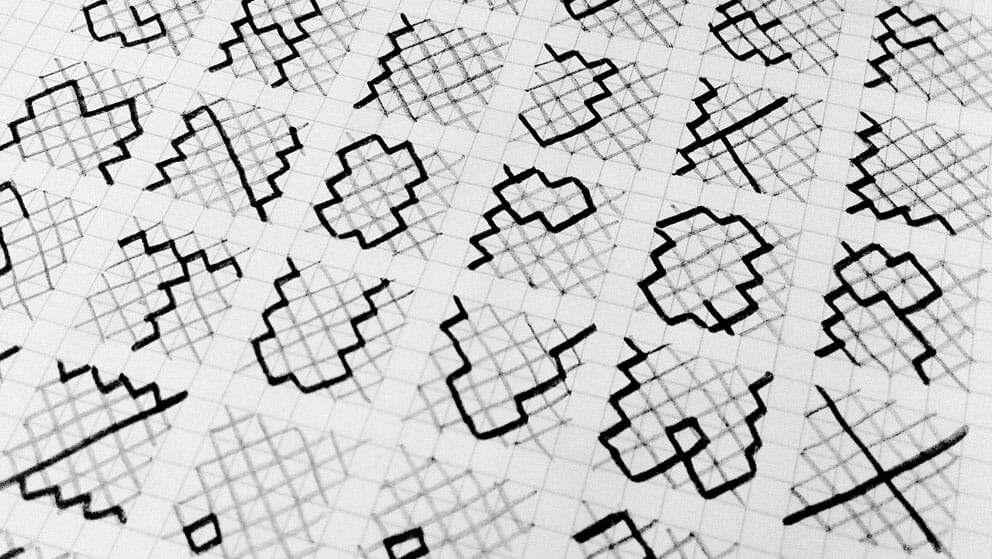
Kathrin Münsch
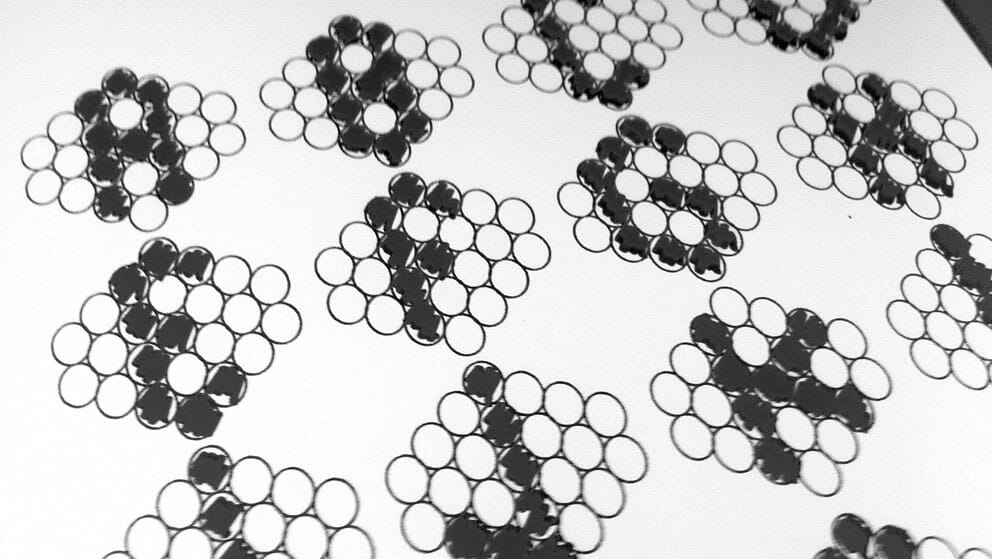
Nadine Hansen
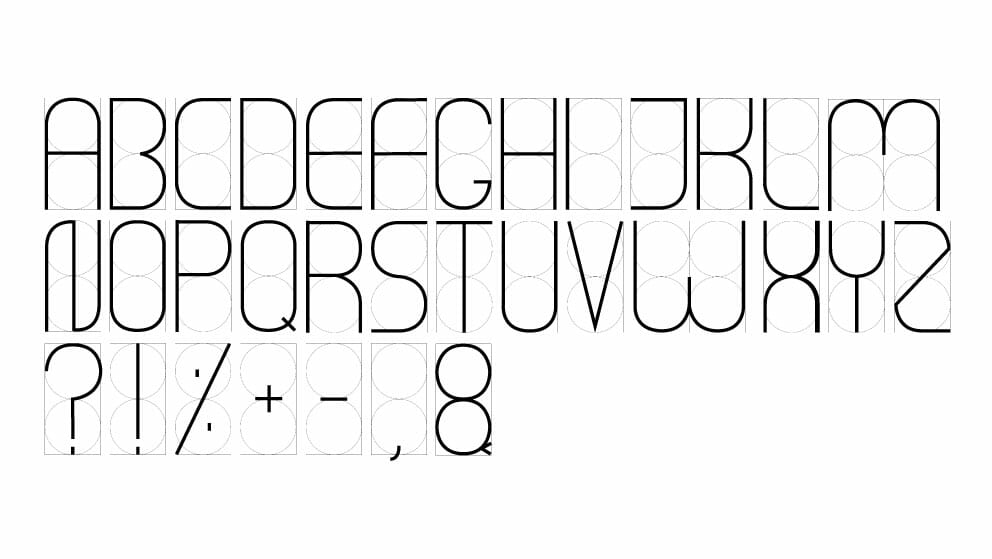
Nina Fuchsberger
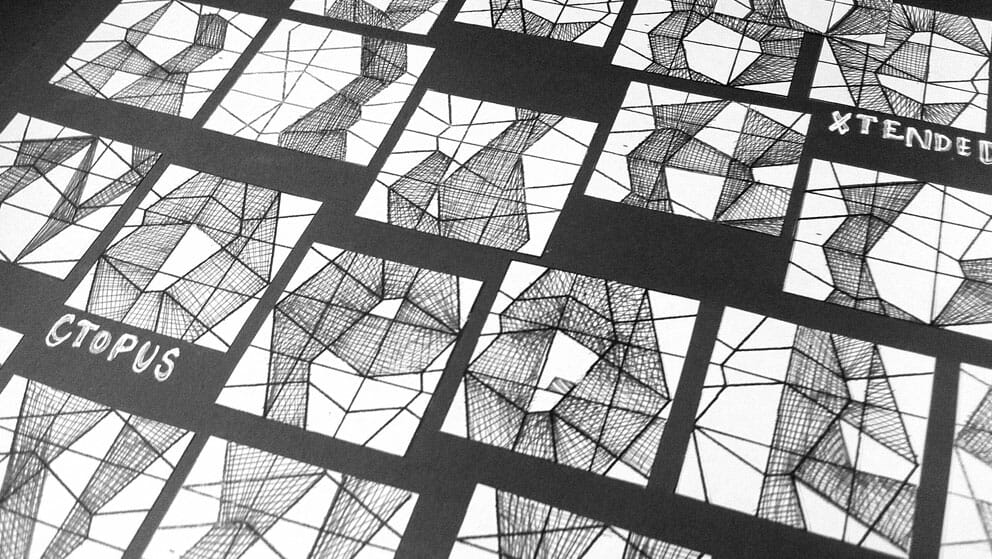
Roman Bauer
Viktoria Tajchmann